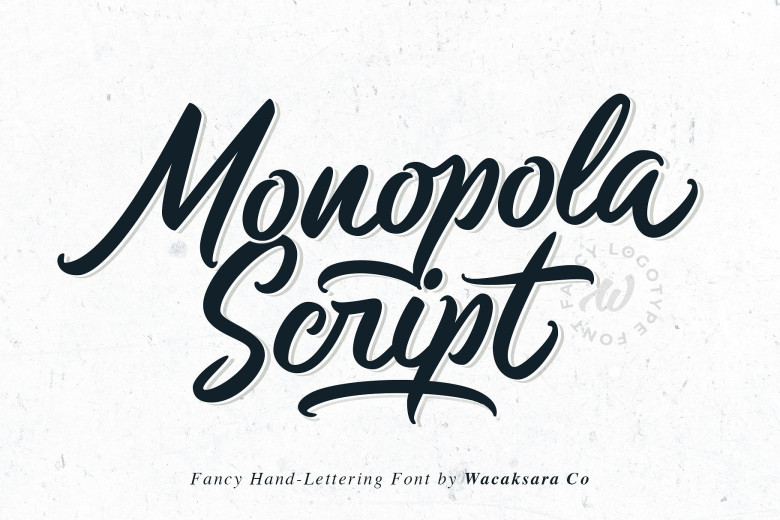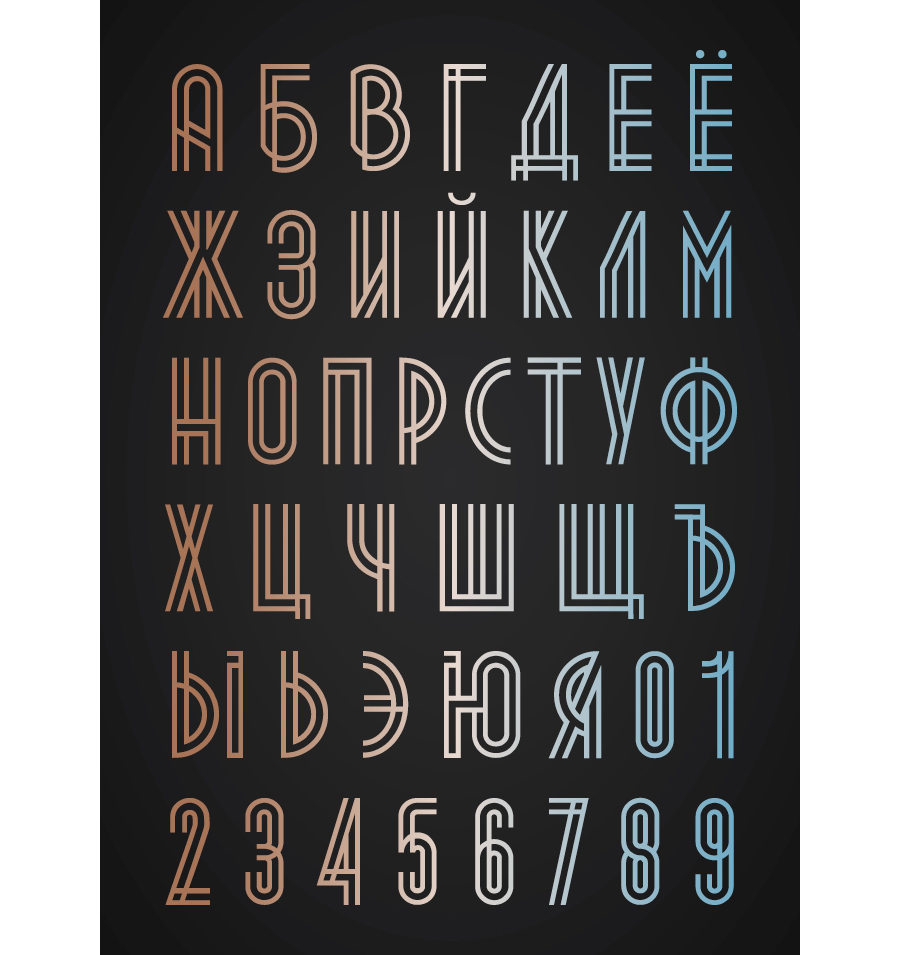
Топ 10 актуальных шрифтов 2021 — Дизайн на vc.ru
При создании дизайна не всегда получается найти тот самый шрифт, который хорошо дополнит композицию. Именно поэтому я сделал свежую подборку из 10 самых актуальных бесплатных шрифтов для вашего проекта в 2021 году.
1. SK Coisa
SK Coisa — декоративный наклонный геометрический шрифт с дерзким характером. Его острые формы и углы, да и вся конструкция вопиют о его необыкновенности. Он необычный и выделяющийся. SK Coisa построен на контрасте округлых и резких геометрических форм, поэтому его внешний вид сложно обойти стороной. Шрифт имеет как заглавные, так и строчные буквы. Он поддерживает базовую, расширенную кириллицу и латинский алфавит, а также многие другие языки и наборы символов. Если вы хотите, чтобы ваш дизайн кричал, то SK Coisa — это именно то, что вам нужно
2. MIGRA
Migra — это шрифт с остроконечными засечками, вдохновленный перелетными птицами.
3. SK Pangramma
SK Pangramma — современный универсальный геометрический шрифт. Для большей универсальности он был разработан в двух стилистических вариациях: Sans Serif и Slab Serif. Гарнитура SK Pangramma названа так, потому что она поддерживает более 200 языков, включая расширенный латинский алфавит, кириллицу и даже греческий. Благодаря широкому набору символов, альтернатив и двум стилистическим вариациям, этот шрифт отлично подходит для дизайн-проектов любой сложности, будь то полиграфическая продукция или веб-дизайн.
4. Barracuda
Barracuda — это новый необычный современный геометрический шрифт без засечек, в котором символы и формы контрастируют по ширине. Шрифт призван нарушить правила и создать неравномерность между круглыми и острыми формами.
5. EIKO
Eiko — бесспорное воплощение элегантности и утонченности. Он вдохновлен работами Эйко Ишиока, талантливой японской художницы, шрифт стремится передать тот же аспект ее работы в этих типографских исследованиях. Шрифт имеет высокую контрастность, так что подойдет для многих проектов.
6. Eskool
Eskool — это бесплатный шрифт, идеально подходящий для заголовков и подзаголовков. Шрифт основан на школьном опыте 90-х годов. Подойдет для оформления образовательных продуктов, заголовков, логотипов и журналов.
7. Italian Inverted Contrast
Blackest — это семейство шрифтов с контрастными засечками, разработанное Франческо Кановаро и Андреа Тартарелли как развитие шрифта Blacker, разработанного Козимо Лоренцо Панчини. Классический скелет и острые края оригинала были сохранены, но при этом контрастность шрифта была сохранена в области так называемых итальянских шрифтов или шрифтов с обратным контрастом.
8. CURRENT
CURRENT — жирный и красивый шрифт без засечек, разработанный Мэттом Пендрилом. Он отлично работает в качестве заголовка на рекламных щитах, плакатах и веб-страницах. Так что, попробуйте его в своем следующем проекте!
9. Sunmora
Sunmora от Ardyana Types — классический декоративный шрифт с засечками с восьмидесятых годов. Это продуманный изгиб и уникальная форма хвоста с 12 весами, от тонкого до жирного. Sunmora идеально подходит для: заголовков, логотипов, дизайна одежды, дизайна веб-сайтов, цветочных изображений, обложек журналов, плакатов и многого другого! Этот шрифт включает произвольные лигатуры. Если вам нужен стильный шрифт, который гарантированно привлекает внимание, то Sunmora справится с этой задачей!
10. Lucky Chang
Lucky Change, Youthlabs Studio, — это новый шрифт с засечками стильной и премиальной формы. Этот шрифт вдохновлен простой и роскошной типографикой. Lucky Change — очень универсальный шрифт, вы можете использовать этот шрифт для различных дизайнов.
Интернет-агентство BINN » 11 лучших современных шрифтов с засечками в 2023 году. Часть 2
Шрифты с засечками помогут сделать ваш дизайн-проект более живым и красивым. В этой части нашей статьи мы продолжим делиться с вами подборкой лучших шрифтов, которые выглядят свежо, смело и интересно. Изучайте нашу подборку и создавайте свои уникальные дизайн-проекты.
Milchella — это элегантный шрифт с засечками, который вы можете использовать для создания дизайнов на тему моды и лайфстайла.
Шрифт имеет стильные и привлекательные буквы тонкого начертания с засечками, что добавит вашему дизайну порцию эстетики и уникальности.
Вы можете использовать этот шрифт для создания современных заголовков для своих веб-проектов. Шрифт включает в себя обычные, полужирные и контурные стили, которые вы можете смешивать и сочетать для создания уникальных дизайнов. Шрифт также включает в себя символы верхнего и нижнего регистра.
Если вы ищете универсальный шрифт с засечками в непринужденном стиле, который подойдет любому проекту — обратите внимание на MAONA. Этот шрифт поставляется с креативным и забавным дизайном букв с крупного размера. В наборе есть как прописные, так и строчные буквы.
49. Luthon Southard Font Duo
Luthon Southand — эффектный дуэтный шрифт со стильными засечками и монотипным шрифтом. Идеально подходит для упаковки, брендинга, журналов, социальных сетей и многого другого.
50. Обычный шрифт Archia
Представляем семейство шрифтов Archia! Archia, разработанная atipo ®. Дизайнер из Хихона/Хиксона, Испания.